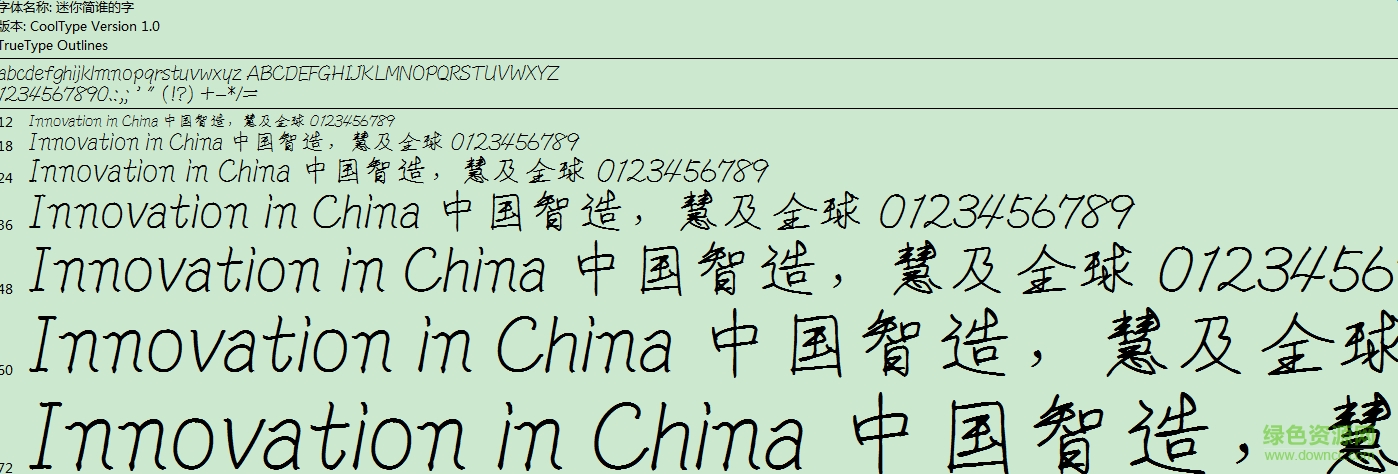
字體神采俊俏,雄渾中流露天真稚拙,典雅中蘊含時代風(fēng)
采,靜中寓動、穩(wěn)中求險、巧拙相生、變化自然,結(jié)構(gòu)嚴
謹,筆法古樸典雅,又極富裝飾意趣。適用于書籍、報
刊、雜志及各類印刷品的標題字或裝飾用字。
字體樸實端正,筆法舒展有力,流暢自然,結(jié)構(gòu)勻稱,適
用于書、報、雜志和各級教材中的小標題及正文字。
字形修長秀美,平正端慶,線條婉轉(zhuǎn)流暢,骨力內(nèi)涵,
挺拔勁健,具有很高的實用性和欣賞性。該字體實用性
強,注重篆法的正確和規(guī)范,注重字形美觀和風(fēng)格的統(tǒng)
其特點是端莊中含瀟灑,凝重中寓自然,字體簡潔明快、
流暢大方、簡繁齊備、雅俗共賞,更接近人們的生活,實
用性很強,特別適用于書寫信函、報告、文章等。